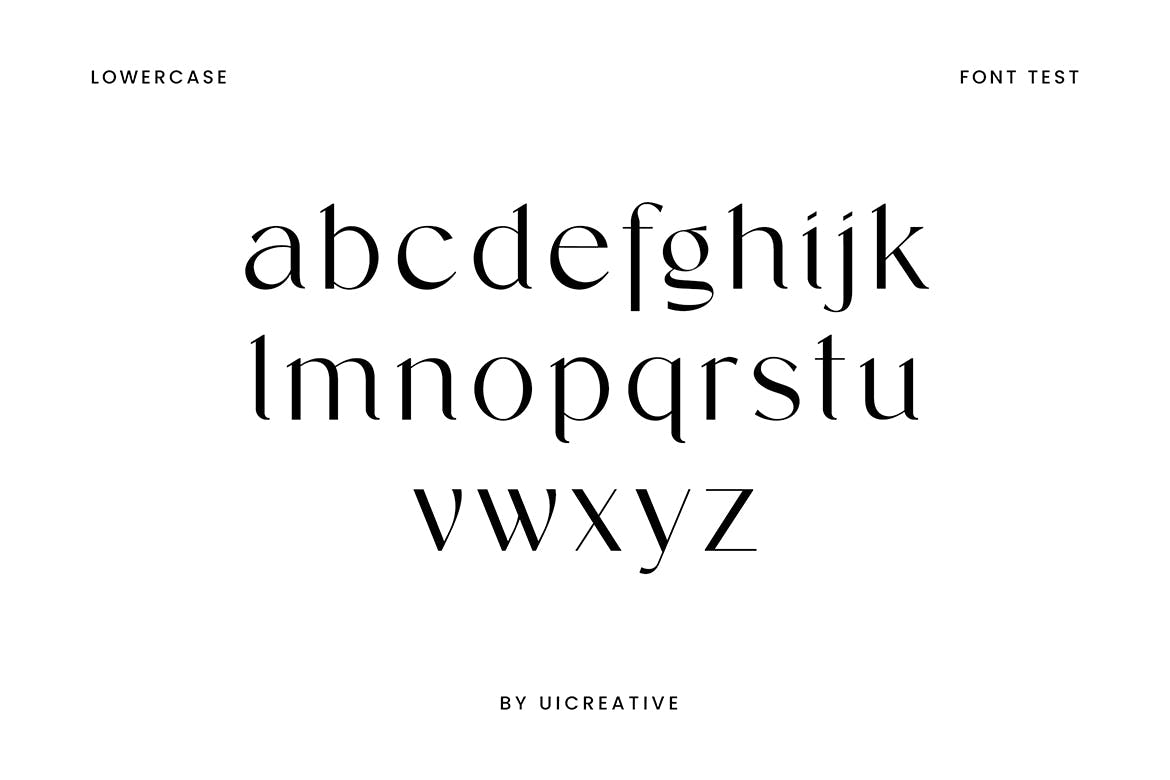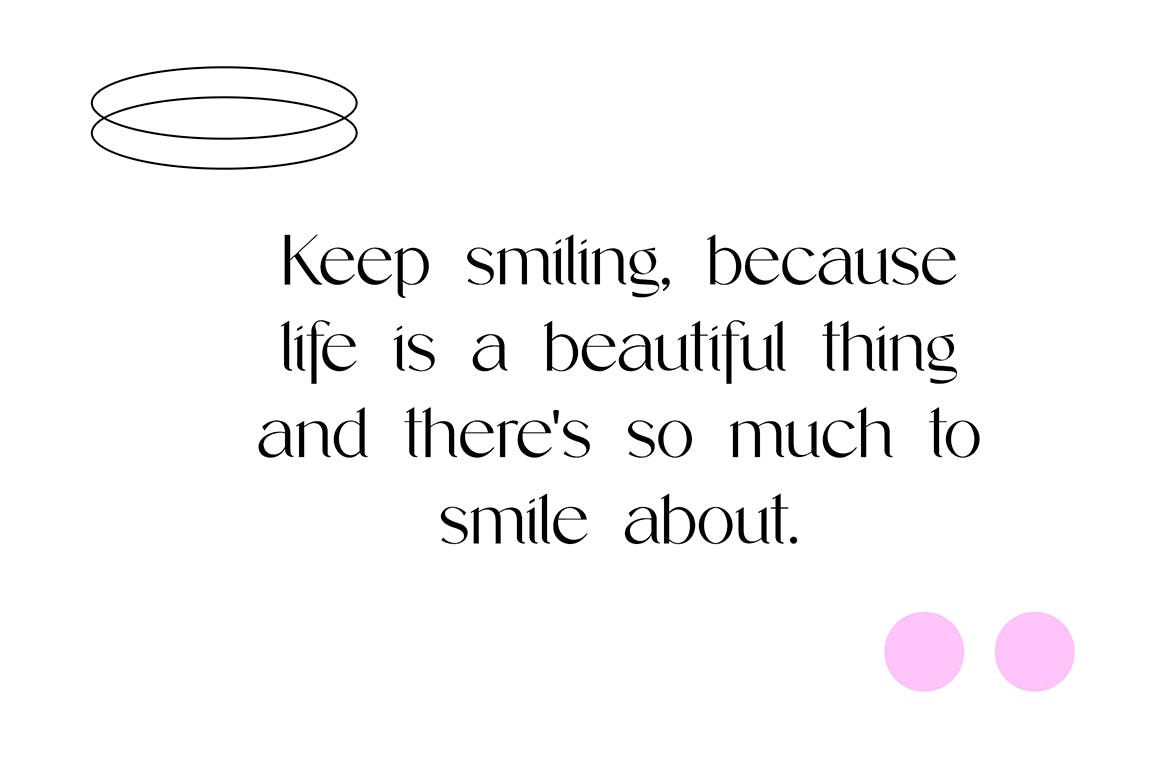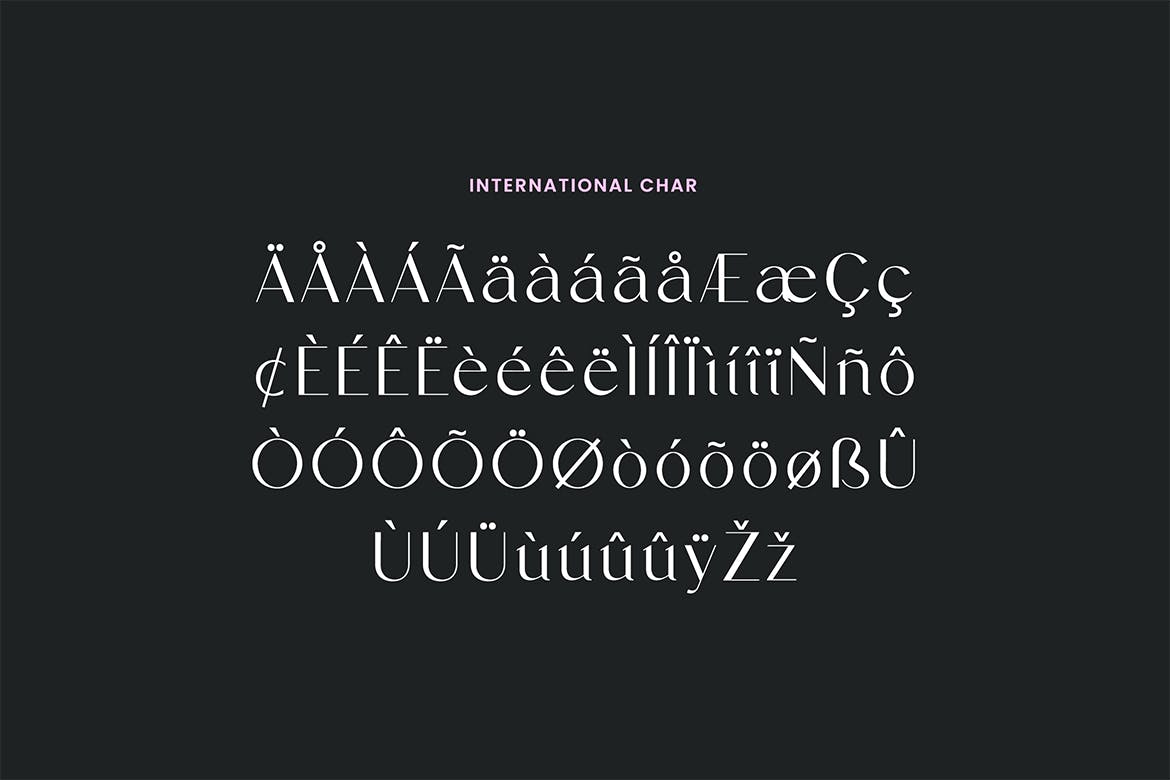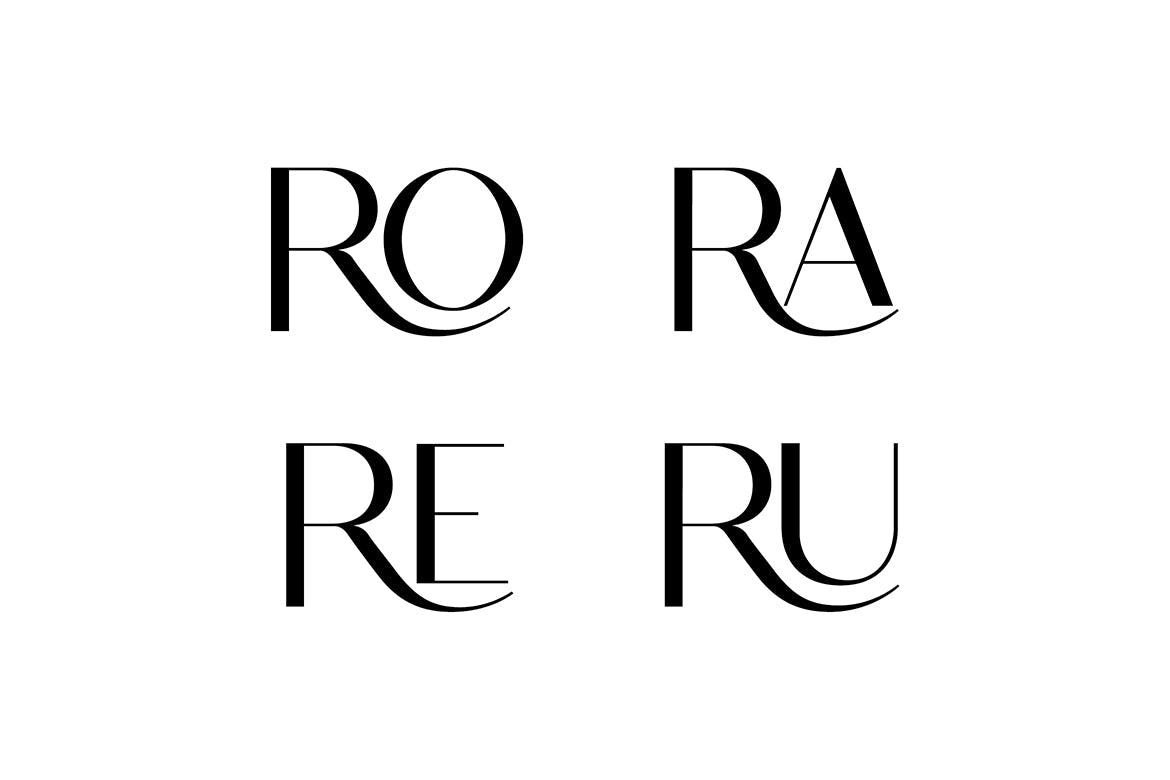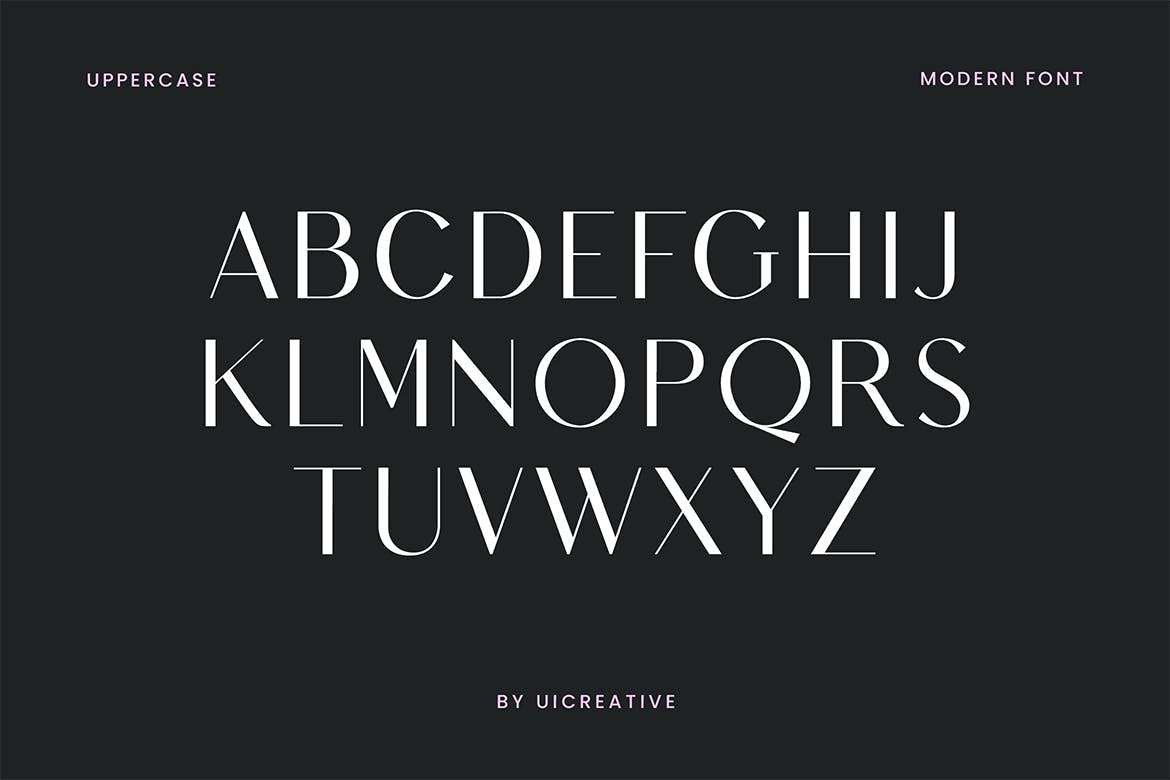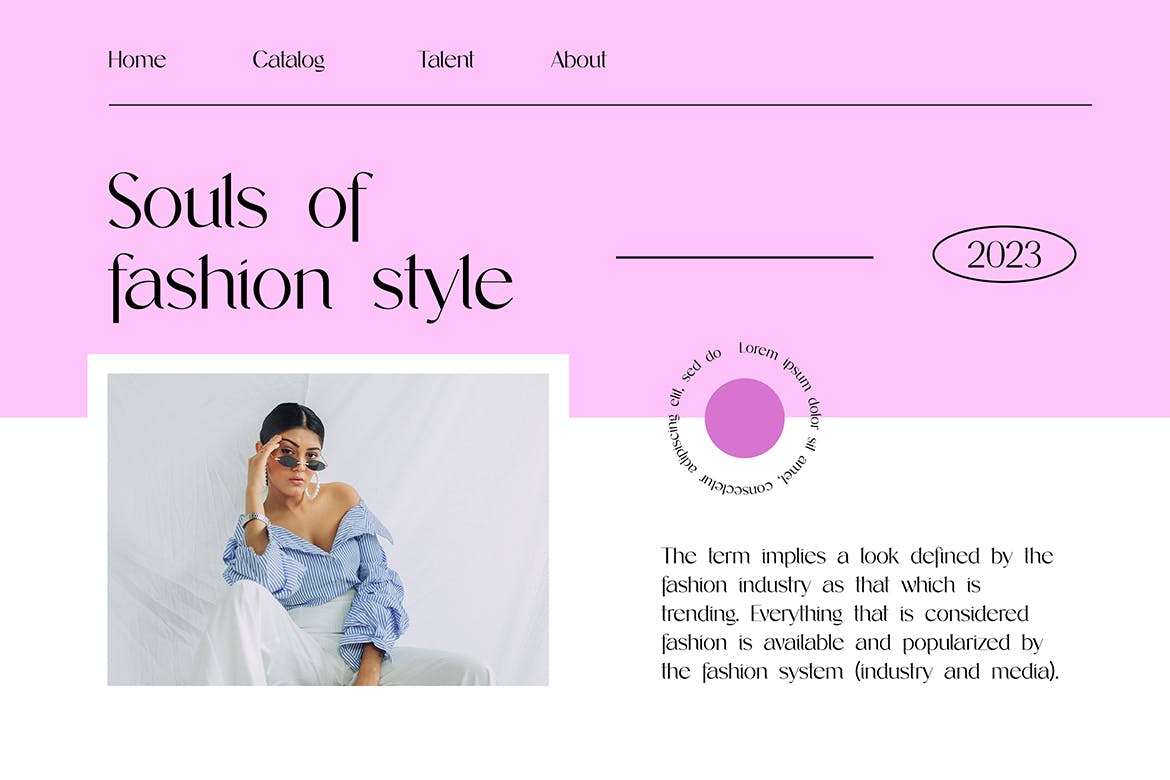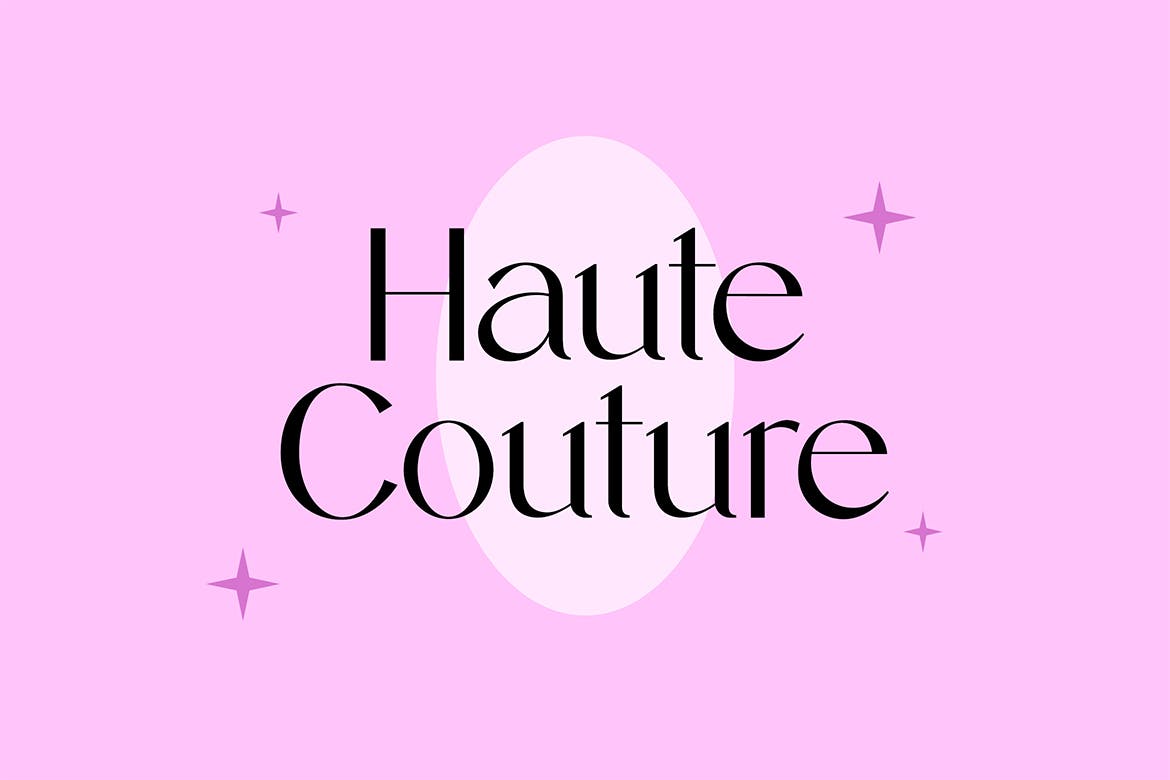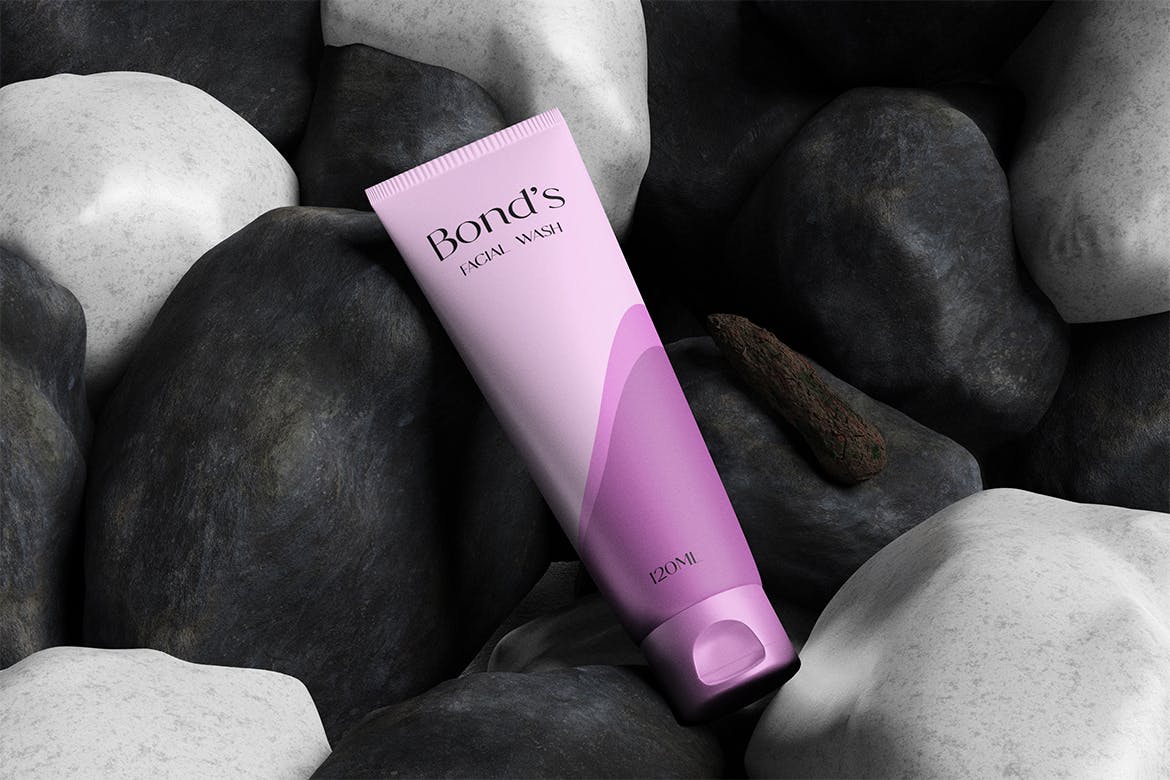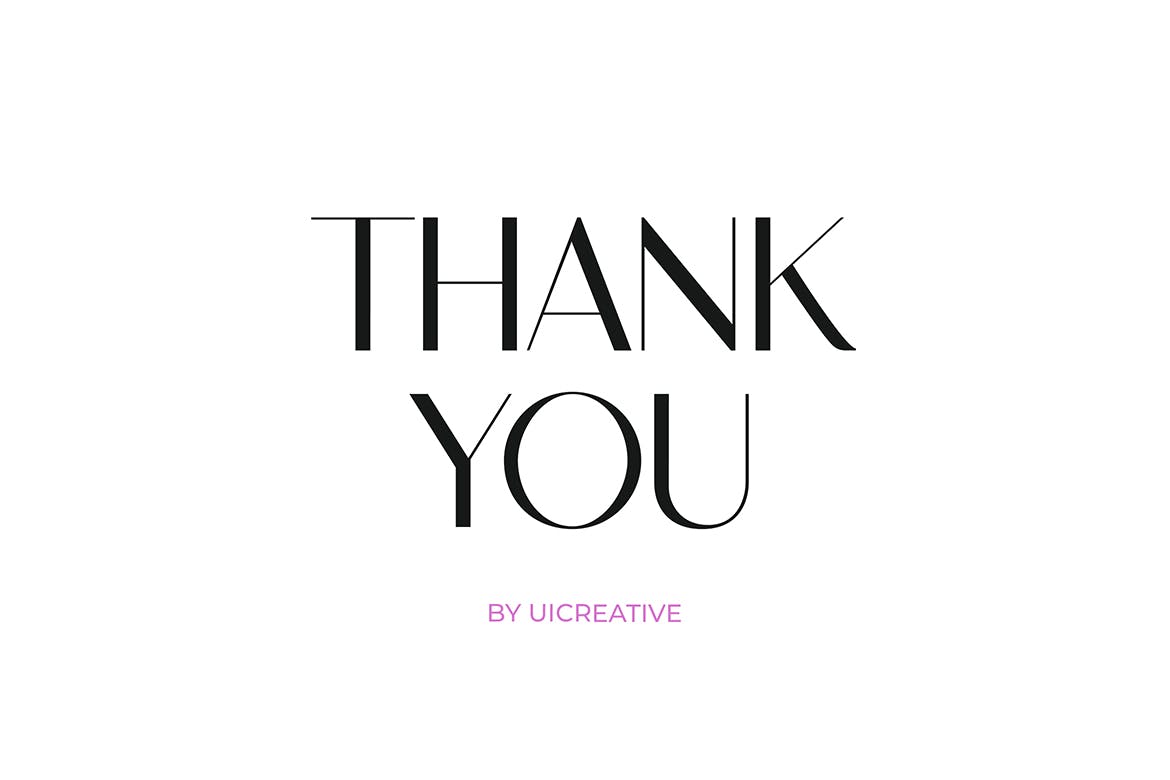
Faithfully Luxury Serif Font
فونت Faithfully Luxury Serif با طراحی زیبا و مدرن، مناسب برای انواع پروژه‌ها.
به شما فونت جدید و جذاب Faithfully Luxury Serif را معرفی می‌کنیم. این فونت سریف مدرن، حسی زیبا، کلاسیک و شیک دارد. این فونت برای انواع پروژه‌ها از جمله امضا، لوازم‌التحریر، لوگو، طراحی عروسی، نقل قول‌های تایپوگرافی، جلد مجلات یا کتاب‌ها، سرصفحه‌های وب‌سایت، لباس، برندینگ، طراحی بسته‌بندی و بیشتر مناسب است. همچنین طراحی‌های مرتبط با مد و برندینگ، کیفیت‌های مردانه و زنانه را به طور همزمان به نمایش می‌گذارد.
کاراکترهای پشتیبانی‌شده:
• ABCDEFoHIJÁLMNOPQRSTUVWXYZ
• abcdefghijklmnopqrstuvwxyz
• 0123456789
• !"#$&'()*+,-./:=?@[]_{|} ¡¢«»¿
• ÀÁÂÃÄÅÇÈÉÊËÌÍÎÏÑÒÓÔÕÖØÙÚÛÜÝ
• àáâãäåçèéêëìíîïñòóôõöøùúûüÿ
• ĀāĂ㥹ĆćĈĊċČčĎďĒēĔĕĖėĘęĚěĜĞğĠġĤĨĩĪī
• ĬĭİıĴĹĽľŁłŃńŇňŌōŎŏŔŘřŚśŜŞşŠšŤ
• ťŨũŪūŬŭŮůŴŶŸŹźŻżŽžǫ
• ȦɢɪɴʀʏʙʜʟᴀᴄᴅᴇᴊᴋᴍᴏᴘᴛᴜᴠᴡᴢẀẂẄẼỲ